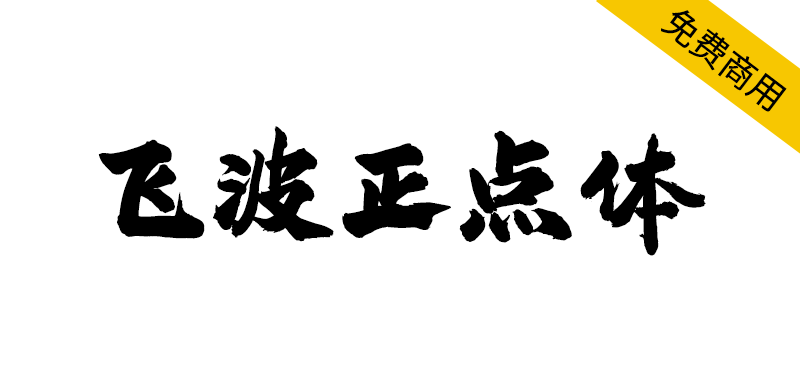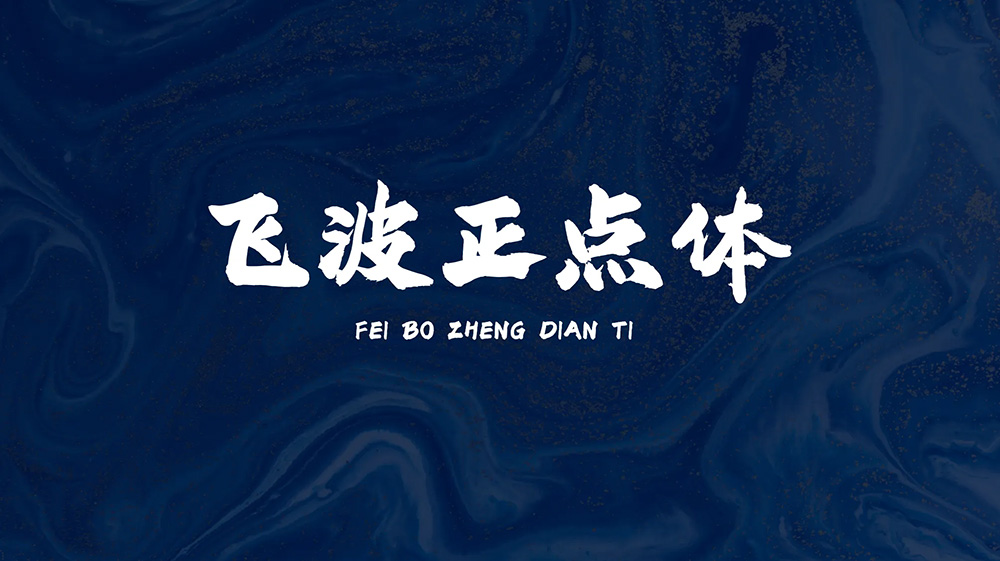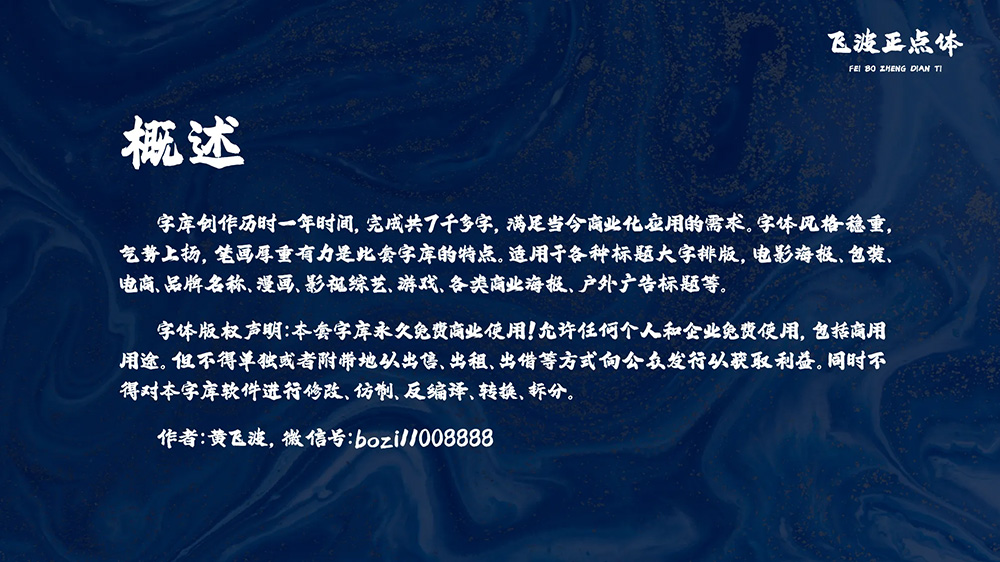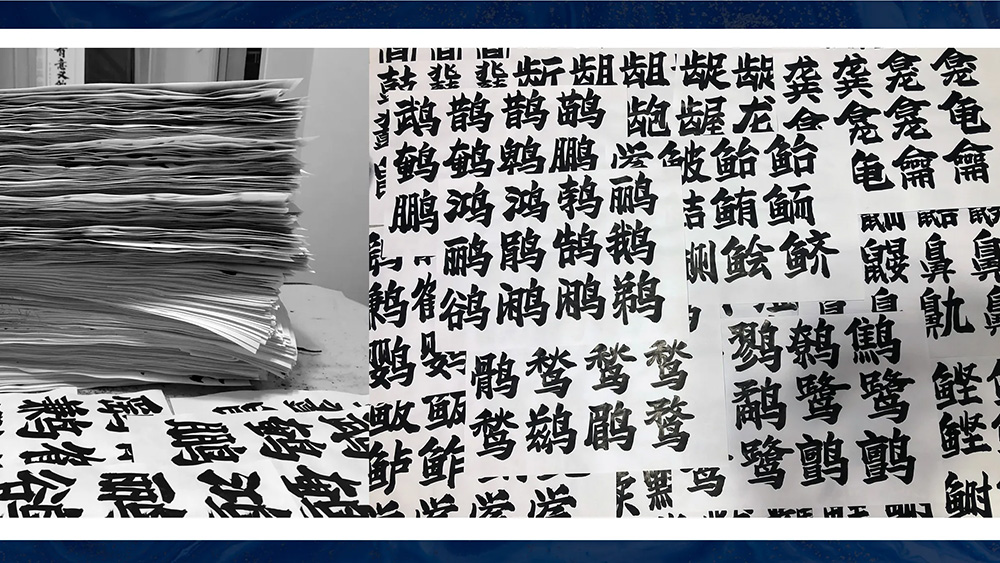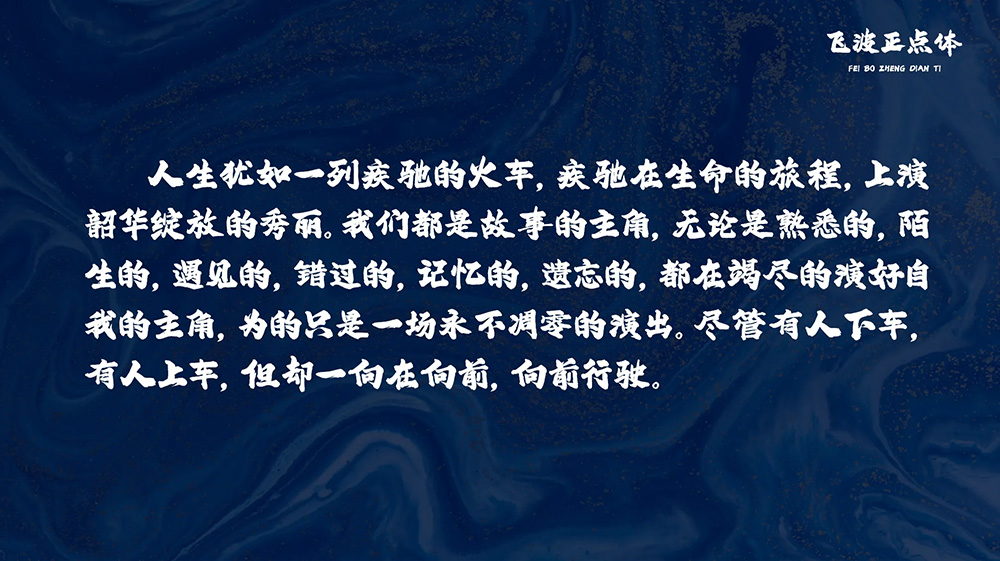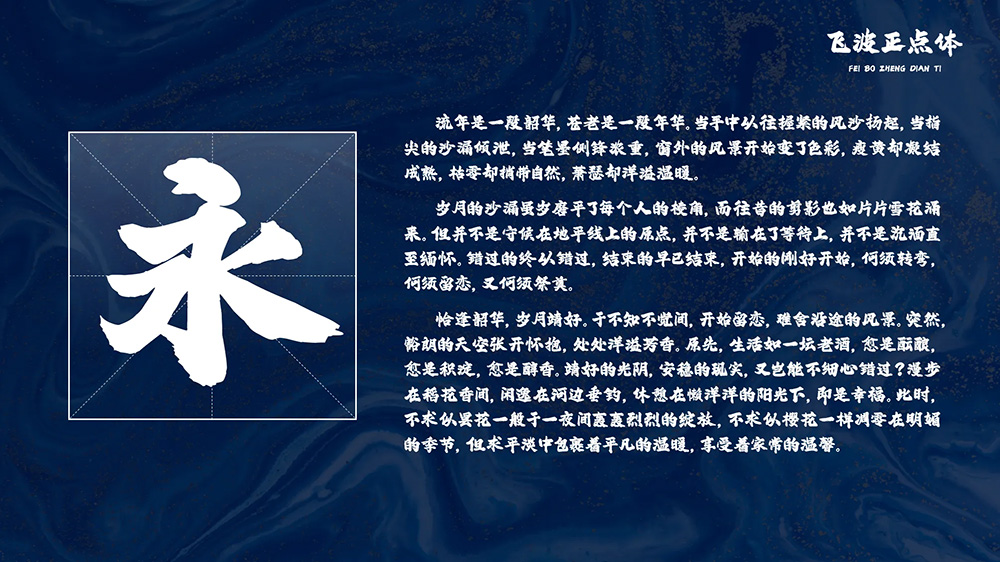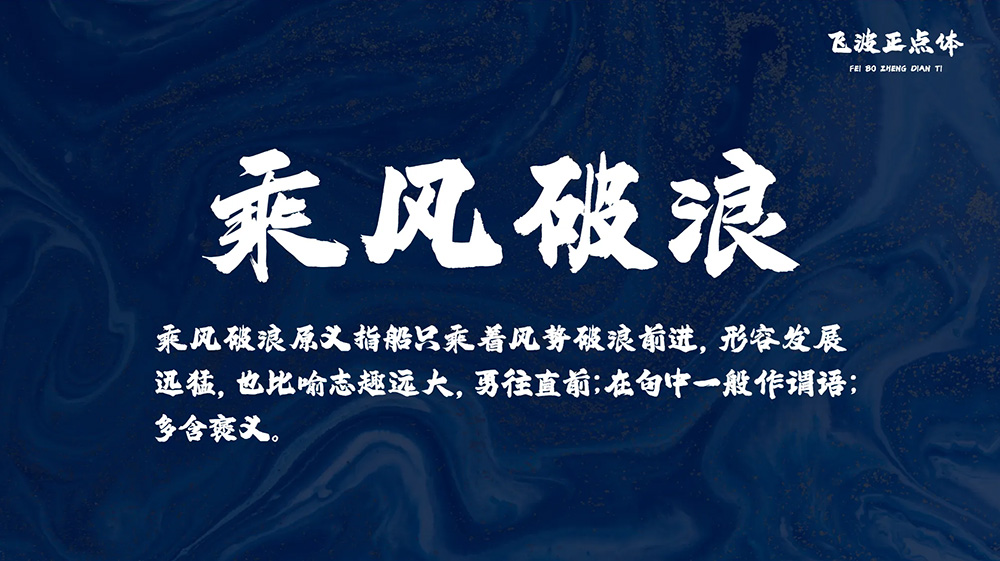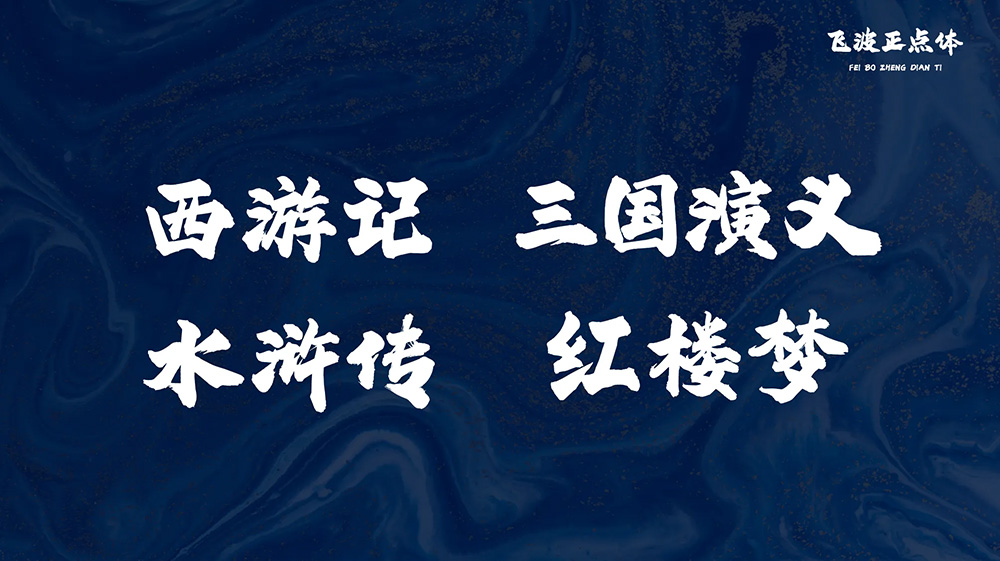
【飞波正点体】字体风格稳重,气势上扬,笔画厚重有力
飞波正点体由本人从毛笔手写到后期软件封装,创作历时一年时间,完成共7千多字。初次制作字库,经验不足之处,欢迎指正。
字体风格稳重,气势上扬,笔画厚重有力是此套字库的特点。适用于各种标题大字排版,电影海报、包装、电商、品牌名称、漫画、影视综艺、游戏、各类商业海报、户外广告标题等。